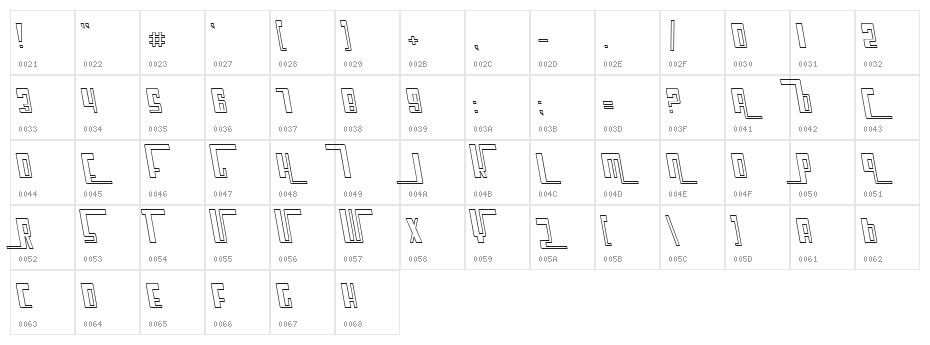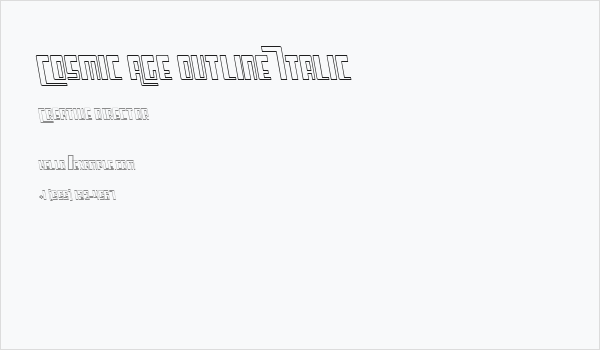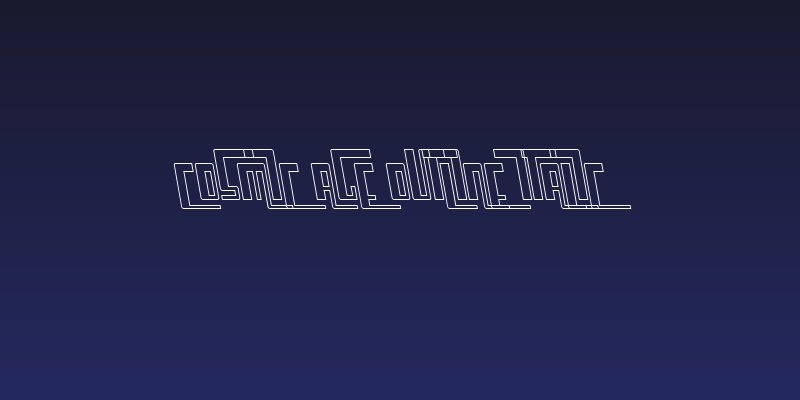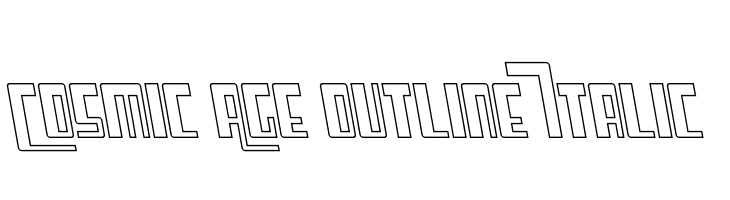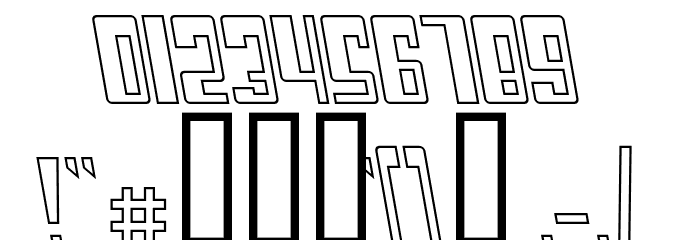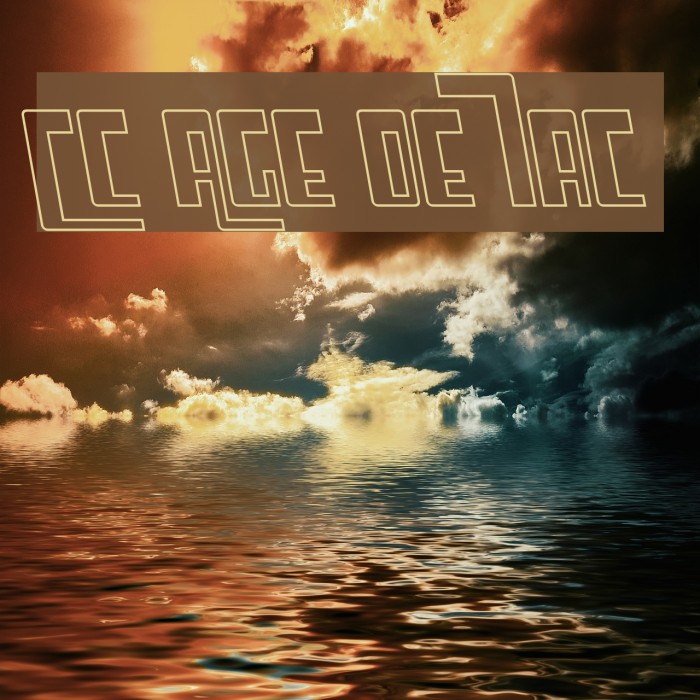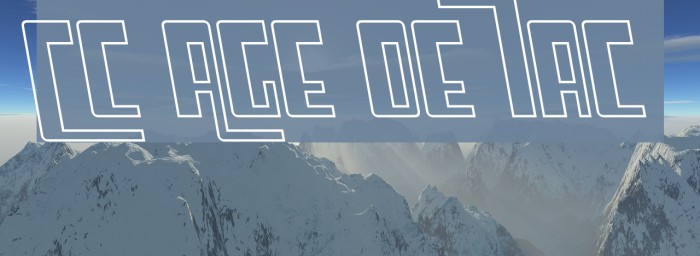
Cosmic Age Outline Italic Font
| Vorgeschlagene Projekte | Ideal for sci-fi themed designs, posters, logos, and digital artwork that require a modern and bold typeface. |